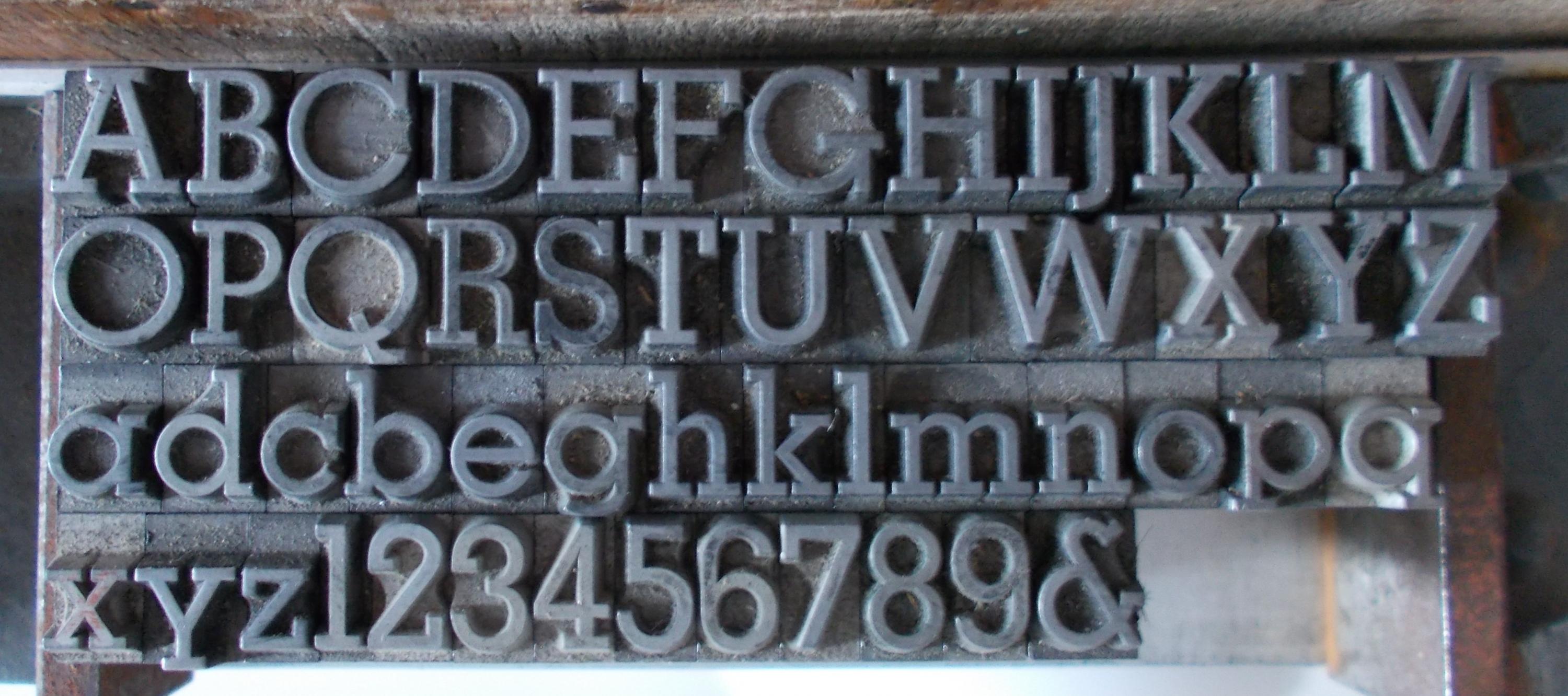
Ist das richtig ?
Was mich etwas stutzig macht: die "fehlenden" Lettern haben eine etwas andere Ligatur (1mm höher) ?!
Ich denke der Unterschied im Schriftbild ist minimal, aber das läßt sich wohl nur im Andruck feststellen.
die "fehlenden" Lettern haben eine etwas andere Ligatur
Ligatur ist eine zusammen gegossene Kombination aus mehreren Buchstaben, z.B. fi
Menno,
ich sollte doch mal mein (Un)wissen auffrischen: ich meinte natürlich die Signatur !!!!!
OK, diese Begriffe sind ja auch nicht mehr soo gängig. Und beim Offsetdruck wird man die auch kaum antreffen, da bekommt man ja schließlich von den jeweiligen Mediengestaltern das fertige Layout.
Menno,
ich sollte doch mal mein (Un)wissen auffrischen: ich meinte natürlich die Signatur
Und genau damit bist Du hier auch richtig, denn neben dem Forum findest du hier auch viele Fachartilel, die all dieses "Gelump" fein ordentlich erklären.
Und dann werden aus "Steckschriften" eben auch "Satzschriften"
Aber generell: Schöne Schriften hast Du da, und wie Du mir ja schon per Mail mitgeteilt hast, können aus denen, die es noch nicht auch digutal gibt, mit Deiner Mitwirkung auch einige digitale Schriften werden. Ich freue mich darauf.
Also keine Sorgen, wenn du aus fehlender Berufserfahrung mal zum falschen Begriff greifst, wir biegen das schon hin!
Was genau meinst du mit : Und dann werden aus "Steckschriften" eben auch "Satzschriften" ?
Im Bleisatz (Hand) gibt es "Liegende Schriften" und "Steckschriften".
Oder meinst du: im digitalen Zeitalter heißt es nur noch Satzschriften ?